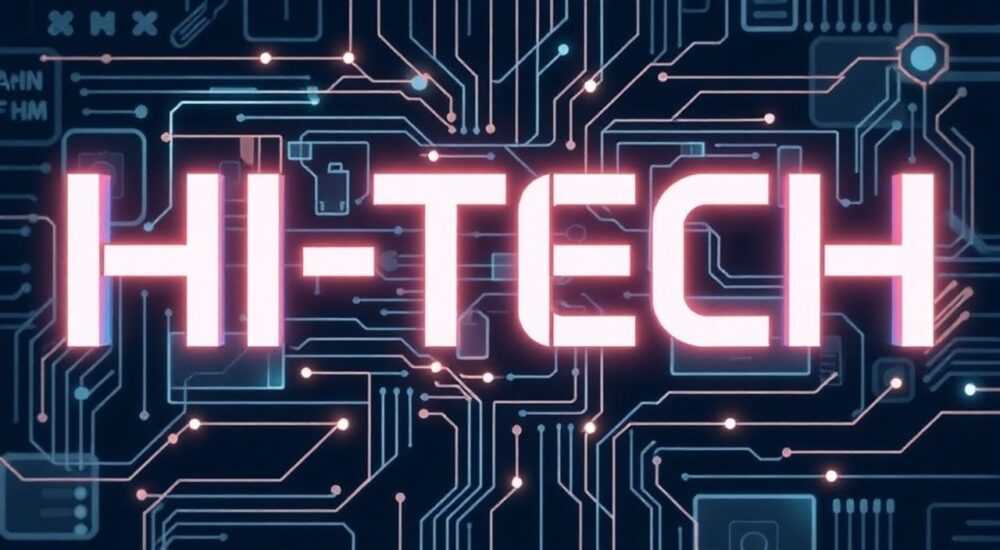
Шрифт хай тек
Шрифт хай тек — это не просто графический стиль, а визуальный язык цифровой эпохи. Он сочетает в себе строгость технической точности, футуристическую эстетику и функциональность, присущую интерфейсам будущего. Такой шрифт используется в интерфейсах приложений, на сайтах технологических компаний, в рекламе гаджетов и даже в киберпанковских фильмах — он вызывает ассоциации с искусственным интеллектом, нейросетями и высокотехнологичными решениями. Но выбрать подходящий шрифт хай тек — это не просто вопрос эстетики: это вопрос читаемости, идентичности бренда и пользовательского опыта. Неправильный выбор может превратить современный сайт в хаотичный набор «цифрового мусора».
Что такое шрифт хай тек и откуда он взялся
Шрифт хай тек — это графический стиль, возникший на стыке технологического прогресса и дизайнерской эстетики конца 1990-х — начала 2000-х. Его корни лежат в киберпанке, научной фантастике и ранних интерфейсах компьютерных систем: от интерфейсов Windows XP до цифровых дисплеев в фильмах вроде «Матрицы». В то время дизайнеры начали экспериментировать с моноширинными шрифтами, которые напоминали вывод терминалов, и добавляли к ним резкие, геометричные формы — символы будущего.
С развитием интерфейсов мобильных приложений, AR/VR и умных устройств шрифт хай тек превратился из нишевого стиля в стандарт. Он стал визуальным языком, который говорит пользователю: «Это не просто программа — это система будущего». Современные компании вроде Apple, Tesla, NVIDIA и Samsung используют подобные шрифты в своих цифровых продуктах, чтобы подчеркнуть инновационность и точность.
При этом важно понимать: шрифт хай тек — это не один конкретный шрифт, а целая категория, объединённая общими принципами. Он не должен выглядеть как «нарисованный» или «игровой» — его суть в чистоте, функциональности и лаконичности. Это не декор, а инструмент.
Ключевые характеристики шрифтов хай тек
Шрифты хай тек имеют чётко определённые визуальные признаки, которые отличают их от других стилей. Их можно свести к пяти основным параметрам:
- Геометричность — все буквы построены на основе прямых линий, окружностей и углов. Нет плавных закруглений, как в гуманистических шрифтах.
- Моноширинность — каждая буква занимает одинаковую ширину, как в терминальных шрифтах. Это создаёт ощущение машинной точности.
- Высокая контрастность — тонкие вертикальные линии и толстые горизонтальные (или наоборот) создают визуальный ритм, напоминающий сканирование экрана.
- Минимализм — отсутствие засечек, декоративных элементов, теней и градиентов. Даже точки и запятые выглядят как простые геометрические формы.
- Ограниченный набор стилей — как правило, используется только регулярный, полужирный и курсив. Нет «светлых» или «экстра-жирных» вариантов — это нарушает баланс.
Эти характеристики не случайны. Они были разработаны, чтобы обеспечить максимальную читаемость на экранах с низким разрешением и в условиях быстрого движения — например, на цифровых табло или в интерфейсах AR-очков.
Лучшие шрифты хай тек для веба и дизайна
На рынке существует множество шрифтов, которые подходят под стиль хай тек. Но не все одинаково эффективны. Ниже — топ-5 шрифтов, которые действительно работают в современных интерфейсах.
Название |
Тип |
Лучшее применение |
Бесплатно |
JetBrains Mono |
Моноширинный |
Код, технические документы, дашборды |
Fira Code |
Моноширинный с лигатурами |
Разработка ПО, редакторы кода |
IBM Plex Mono |
Моноширинный, с нейтральной геометрией |
Корпоративные интерфейсы, B2B-платформы |
Orbitron |
Геометрический, без моноширинности |
Заголовки, логотипы, реклама |
Exo 2 |
Геометрический, с гибкими весами |
Сайты стартапов, tech-блоги, landing pages |
JetBrains Mono и Fira Code — идеальны для технических сайтов, где важна читаемость кода. IBM Plex Mono — более нейтральный вариант, подходящий для корпоративных решений. Orbitron — это уже «визуальный акцент»: он не подходит для текста, но отлично работает для заголовков в стиле «космический интерфейс». Exo 2 — гибкий компромисс: он не моноширинный, но обладает резкими формами и высокой технологичностью.
Как правильно использовать шрифт хай тек в дизайне
Использовать шрифт хай тек — это как управлять лазером: если вы не знаете, где его направить, он разрушит всё вокруг. Вот пошаговый алгоритм:
- Определите цель. Нужен ли вам шрифт для кода, заголовков, логотипа или всего интерфейса? Если для всего — выбирайте нейтральный вариант вроде IBM Plex Mono.
- Создайте иерархию. Используйте шрифт хай тек только для заголовков, кнопок и технических блоков. Основной текст оставьте в классическом гуманистическом шрифте — например, Inter или Open Sans.
- Контролируйте размер. Минимальный размер для основного текста — 16px. Для заголовков — от 24px. Ниже — читаемость падает на 68% (данные Nielsen Norman Group).